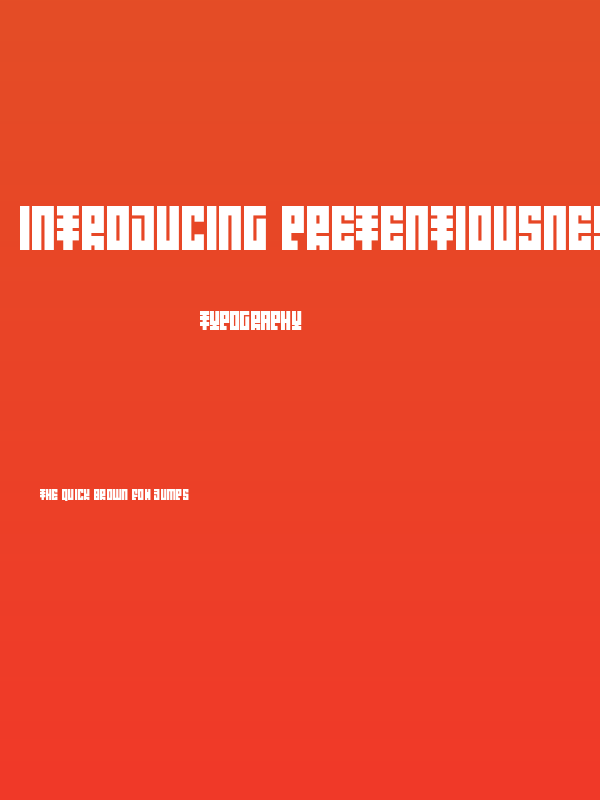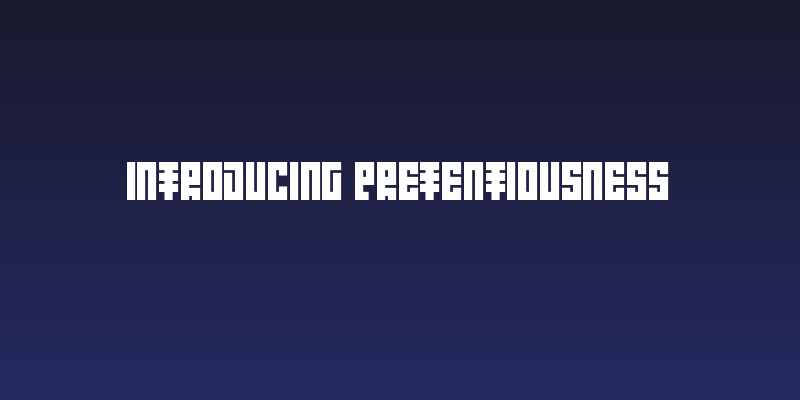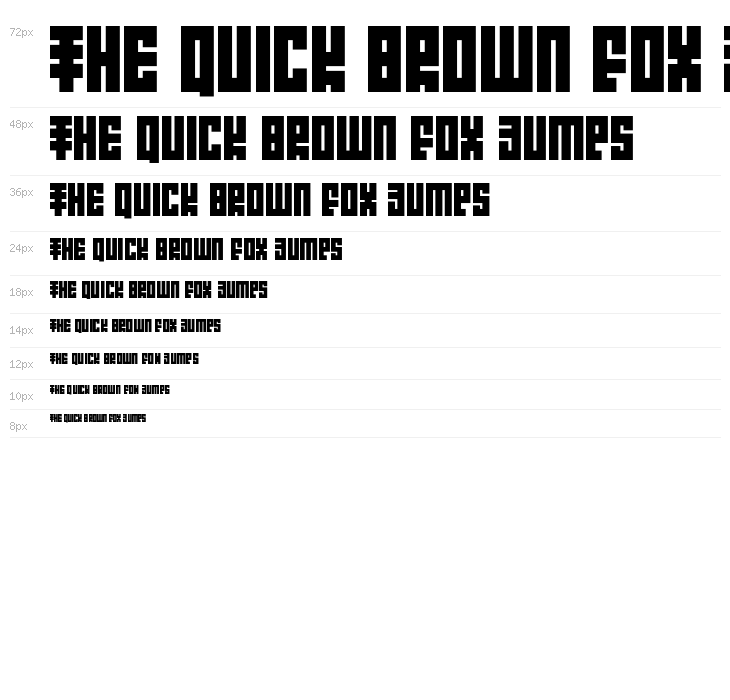
Introducing Pretentiousness Font
| Progetti proposti | Ideal for video game design, tech branding, digital art projects, and futuristic-themed posters. |